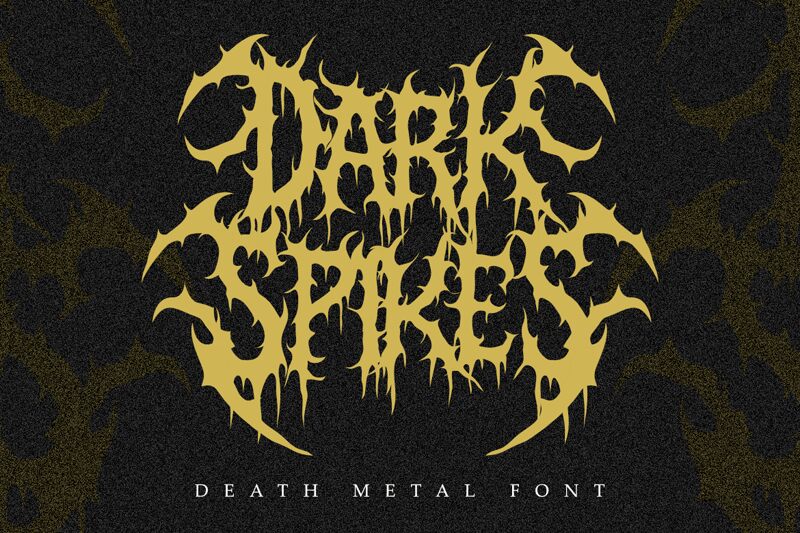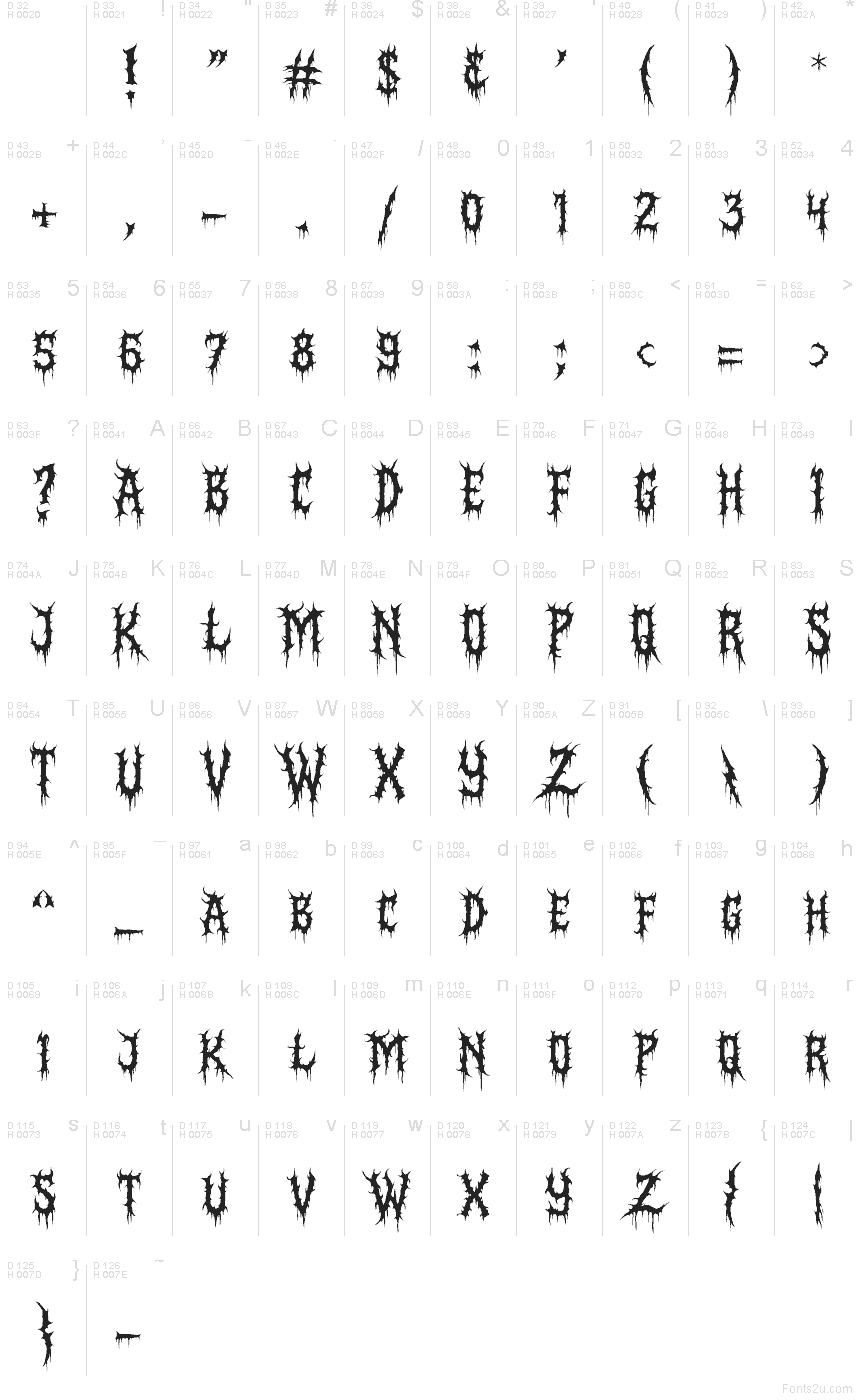
Písmo Dark Spikes od Masyafi Studio je bezplatný gotický font se zubatými, trnitými tahy a dlouhými kapajícími konci, které dodávají písmenům potrhaný a ostrý vzhled. Tvary působí nahuštěně a nepravidelně, s ostrými výřezy a špičatými vrcholy, což celý design ukotvuje v temném stylu vhodném pro nadpisy.
Dark Spikes skvěle funguje u hororových plakátů, vizuálů metalových kapel, názvů her, akčních letáků a halloweenové grafiky, kde tyto rozbité hrany nesou hlavní téma ještě před přidáním barev nebo dekorací. Tento bezplatný font se také hodí pro loga, obaly alb a krátké texty, když hledáte gotický akcent s drsným, ručně řezaným charakterem.